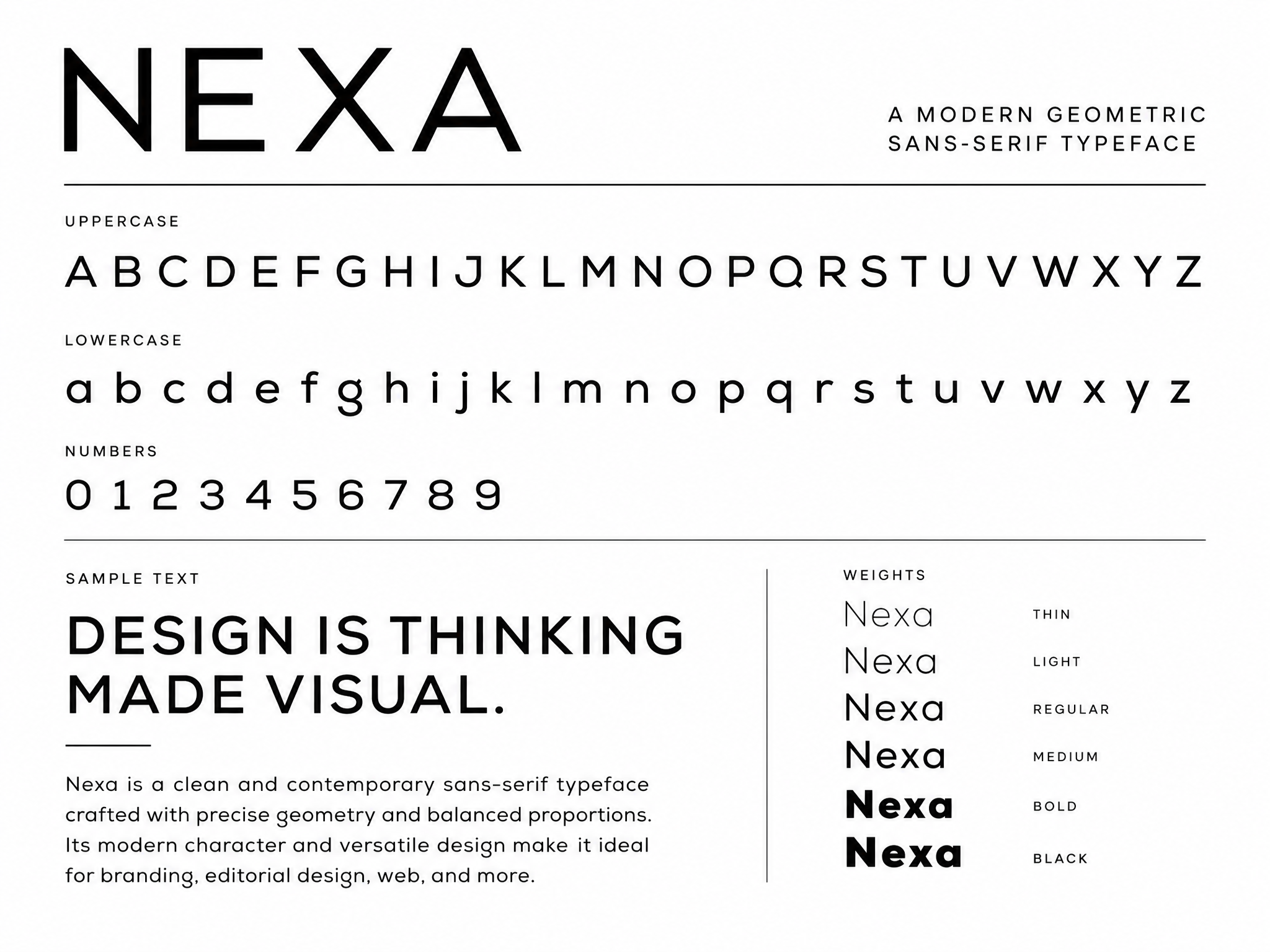
Modern Geometrik Sans Serif Font Ailesi; logo tasarımı, kurumsal kimlik, başlık ve web arayüzleri için titizlikle çizilmiş çok yönlü bir font koleksiyonudur. Geometrik iskeleti sayesinde hem büyük puntolarda hem de küçük metin bloklarında yüksek okunabilirlik sunar. Paket; Thin, Light, Regular, Medium, Bold ve Black olmak üzere altı farklı ağırlık içerir. Bu sayede tek bir font ailesiyle güçlü bir görsel hiyerarşi kurabilirsiniz. Tüm karakterler Türkçe karakter setini (ç, ğ, ı, İ, ö, ş, ü) eksiksiz destekler. Dosya formatları: OTF, TTF ve web kullanımı için WOFF. Ticari ve kişisel projelerde kullanıma uygundur. Kurumsal sunumlardan sosyal medya görsellerine, ambalaj tasarımından mobil uygulama arayüzlerine kadar geniş bir kullanım alanı bulacaksınız.
Modern Geometrik Sans Serif Font Ailesi